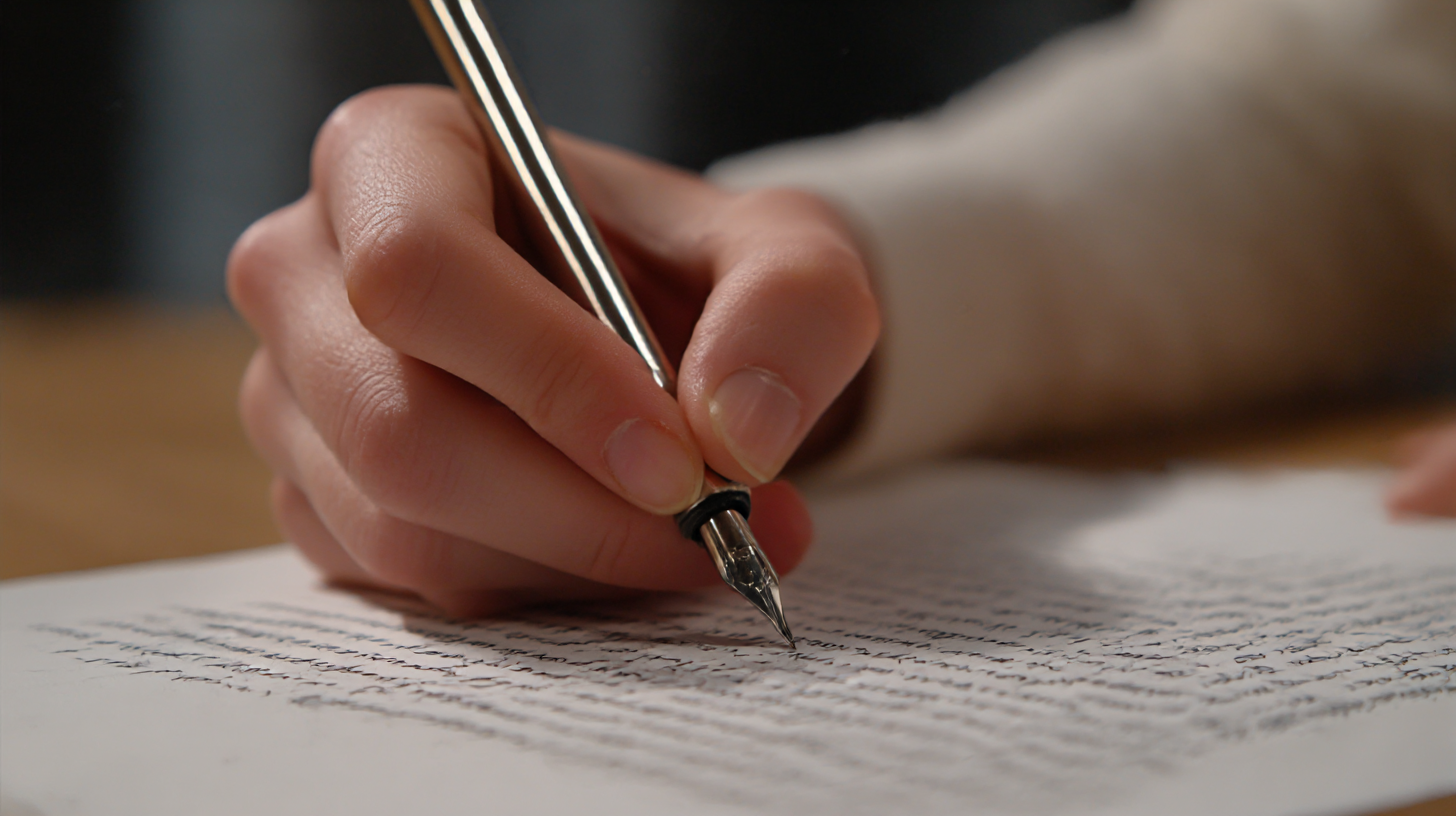
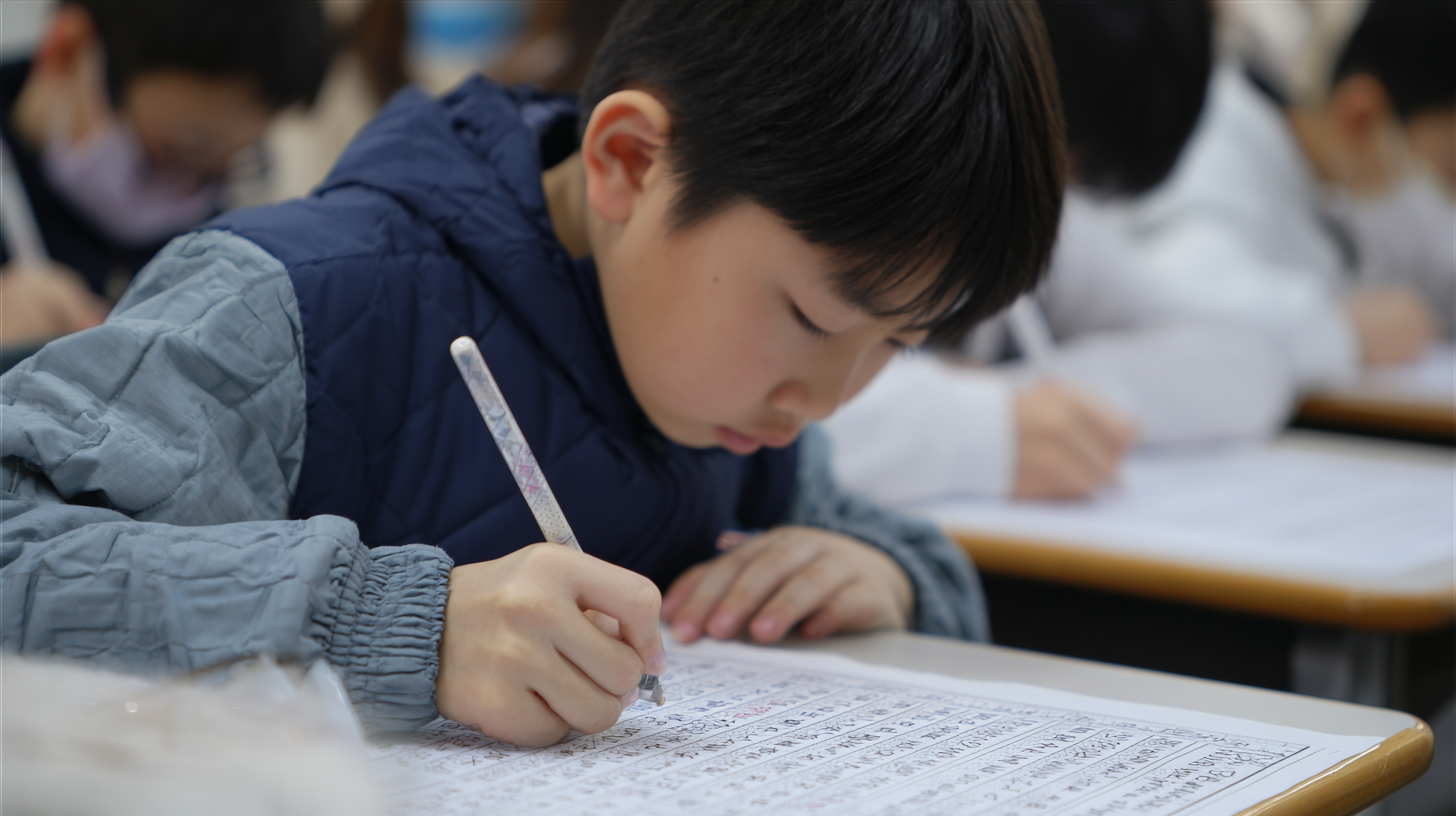
글씨 교정 - 초등학생 때부터 시작해야 하는 이유 아이들의 글씨체는 초등학생 시기에 형성되기 시작해요. 이때 잘못된 습관이 들면 어른이 되어서도 글씨를 교정하기 어려워질 수 있어요. 🖊
어릴 때부터 글씨를 바르게 쓰는 연습을 하면 평생 예쁜 글씨체를 유지할 수 있을 뿐만 아니라, 집중력과 학습 능력 향상에도 도움이 된답니다! ✍
그렇다면 초등학생 때 글씨 교정을 시작해야 하는 이유와 효과적인 연습 방법에 대해 알아볼까요? 🚀
📝 초등학생 시기의 글씨체 형성 과정
초등학생 시기는 손글씨가 본격적으로 형성되는 중요한 시기예요. 이때 바른 필기 습관을 들이면 평생 깔끔한 글씨체를 유지할 수 있답니다! ✍
보통 아이들은 만 4~5세 무렵부터 글자를 따라 쓰기 시작해요. 하지만 이때는 아직 손 근육이 완전히 발달하지 않아 글씨가 삐뚤빼뚤할 수밖에 없어요. 초등학교에 입학하면서부터 본격적으로 글씨를 배우고, 이 시기에 올바른 글쓰기 습관을 들이는 것이 매우 중요해요. 📚
초등 저학년(1~2학년) 때는 손가락 힘을 기르고 획을 정확하게 긋는 연습을 많이 해야 해요. 고학년(3~6학년)이 되면 글씨를 빠르게 써야 할 일이 많아지므로 이 시기까지는 글씨의 균형과 가독성을 높이는 연습을 충분히 해두는 것이 좋아요. ✏
📊 초등학생 글씨체 발달 과정
연령 특징 추천 연습법 4~5세 기본적인 선과 원 그리기 가능 색칠하기, 점 잇기 놀이 6~7세 글자를 따라 쓰기 시작 획을 정확히 긋는 연습 8~9세 (초등 저학년) 글씨체가 점차 안정됨 글자 크기와 간격 맞추기 연습 10~12세 (초등 고학년) 필기 속도가 빨라지며 글씨체 습관이 고정됨 균형 잡힌 필기 연습, 필사하기 초등학생 시기에 글씨 연습을 충분히 하면 성인이 되어서도 깔끔한 필체를 유지할 수 있어요. 😊 그렇다면 왜 초등학생 때부터 글씨 교정을 시작해야 할까요? 다음에서 알아볼게요! 🚀
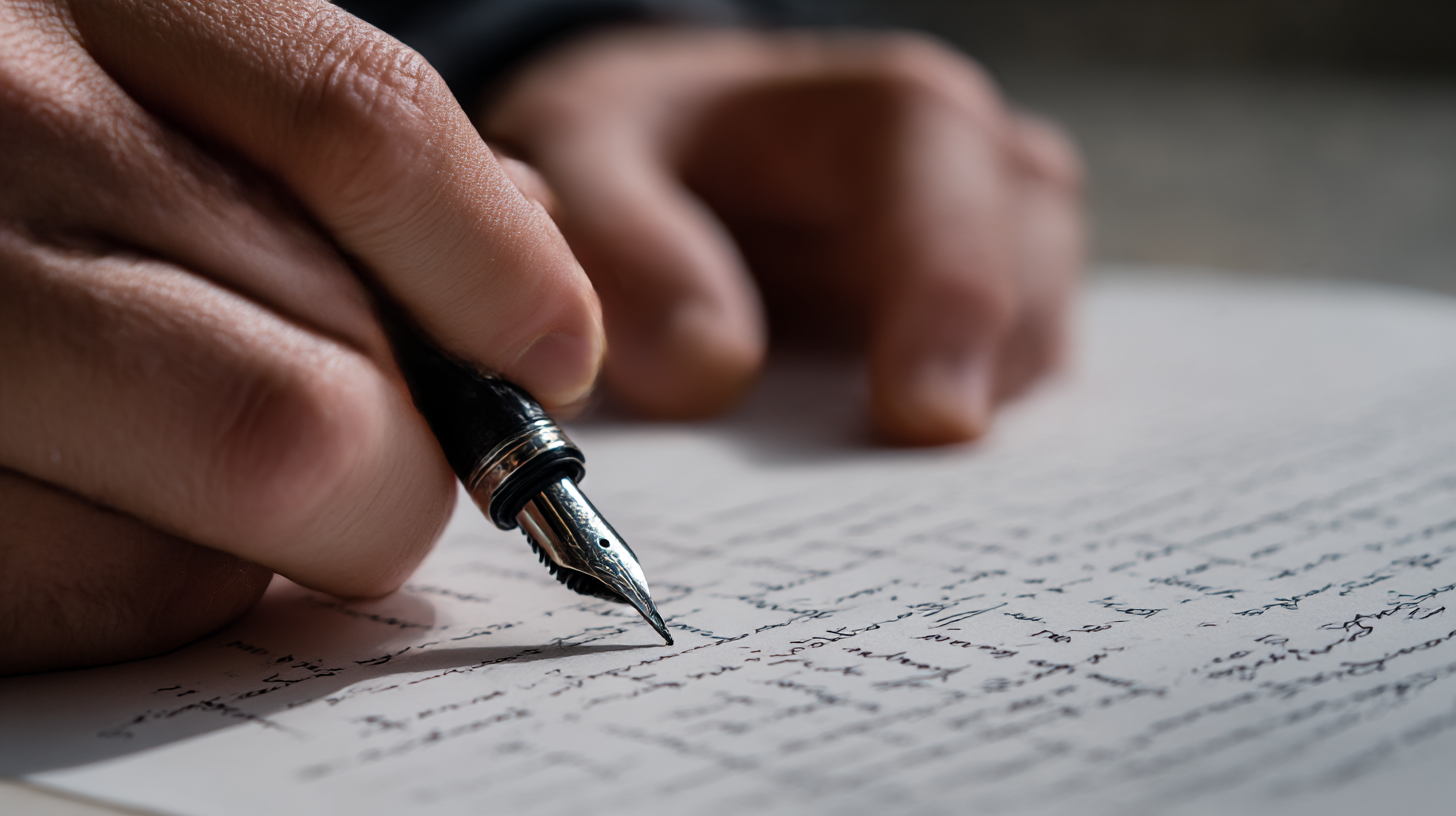
초등학생 시기의 글씨체 형성 과정 🎯 어릴 때 글씨 교정을 시작해야 하는 이유
글씨 교정은 빠르면 빠를수록 좋아요! 특히 초등학생 시기에 바른 필기 습관을 들이면 성인이 되어서도 예쁜 글씨체를 유지할 수 있답니다. ✍
어릴 때 글씨를 교정해야 하는 가장 큰 이유는 '근육 기억'과 '필기 습관'이 형성되기 때문이에요. 글씨를 쓰는 것은 단순한 손 움직임이 아니라 손과 뇌가 연결된 하나의 패턴이에요. 🧠✋
즉, 초등학생 때 글씨를 잘못된 방식으로 쓰기 시작하면 그 습관이 그대로 굳어버려서 나중에 교정하기가 더 어려워져요. 반대로, 어릴 때부터 바른 글씨체를 익히면 오랫동안 유지할 수 있어요. 😊
📌 어릴 때 글씨 교정을 하면 좋은 점
이유 설명 근육 기억 형성 손이 자연스럽게 올바른 글씨체를 기억함 필기 속도 향상 글씨를 빠르고 정확하게 쓸 수 있음 자신감 증가 깔끔한 글씨로 인해 학습에 대한 자신감 상승 평생 유지 가능 한 번 익힌 글씨체는 쉽게 바뀌지 않음 이처럼 어릴 때부터 글씨를 교정하면 시간이 지나도 변하지 않는 좋은 습관을 가질 수 있어요. 그렇다면 초등학생들이 효과적으로 글씨를 교정하는 방법은 무엇일까요? 🎯
📖 초등학생을 위한 효과적인 글씨 교정법
초등학생이 글씨를 교정하려면 단순히 많이 써보는 것만으로는 부족해요. 올바른 방법으로 꾸준히 연습해야 손에 익고, 자연스럽게 예쁜 글씨체가 형성된답니다! ✍
특히 어린아이들은 손 근육이 아직 완전히 발달하지 않았기 때문에 글씨를 쓸 때 힘 조절이 어렵고, 쉽게 피곤해질 수 있어요. 그래서 글씨 연습을 할 때는 재미있고, 무리 없는 방법으로 접근하는 것이 중요해요! 😊
✏ 효과적인 초등학생 글씨 교정법
연습법 방법 효과 점선 따라 쓰기 글자의 점선을 따라 쓰면서 형태 익히기 획의 방향과 균형 익히기 모눈 종이에 쓰기 모눈 칸을 활용해 글자 크기와 간격 맞추기 균형 잡힌 글씨체 연습 큰 글씨부터 작은 글씨로 처음에는 크게 쓰고 점점 작은 글씨로 연습 손 근력 강화 & 글씨 조절 능력 향상 필사 연습 짧은 문장을 따라 쓰면서 글씨체 익히기 자연스러운 필기체 형성 이러한 연습법을 활용하면 초등학생도 재미있게 글씨를 교정할 수 있어요! 그렇다면 글씨체를 예쁘게 유지하려면 어떤 필기 습관을 가져야 할까요? 🎯
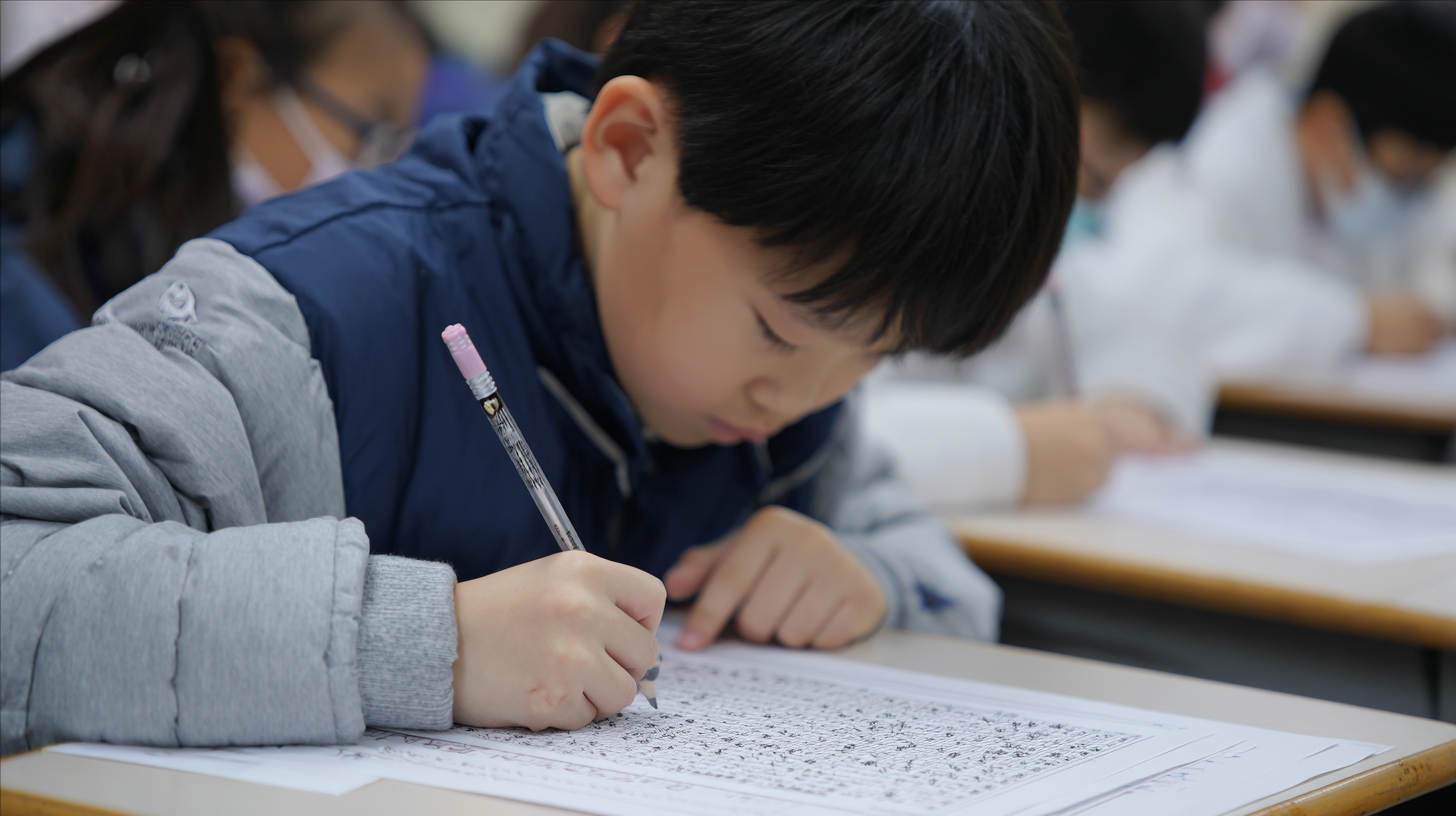
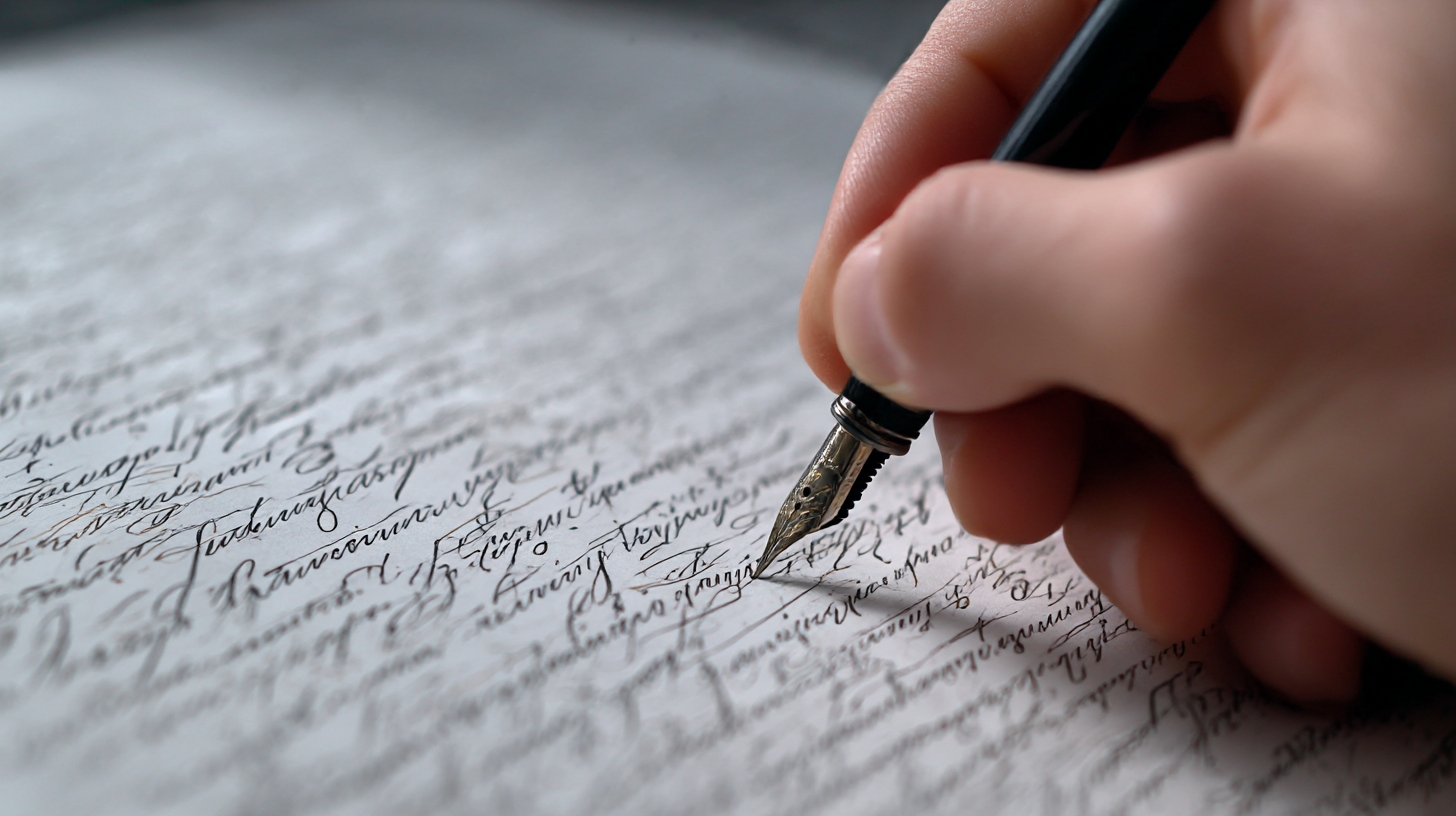
초등학생을 위한 효과적인 글씨 교정법 📌 바른 글씨체를 위한 필기 습관
예쁜 글씨를 쓰려면 올바른 필기 습관을 갖는 것이 중요해요. 아무리 많은 연습을 해도 필기 습관이 잘못되어 있다면 글씨가 쉽게 흐트러지고, 일정한 글씨체를 유지하기 어려워요! ✍
특히 초등학생들은 글씨를 빠르게 쓰려고 하다가 손에 힘이 너무 많이 들어가거나, 바른 자세를 유지하지 못하는 경우가 많아요. 따라서 필기 습관을 교정하는 것이 예쁜 글씨체의 첫걸음이에요. 😊
📝 올바른 필기 습관 체크리스트
필기 습관 설명 효과 바른 자세 유지 허리를 곧게 펴고, 책상과 눈의 거리를 일정하게 유지 손목 피로 감소 & 글씨 안정성 향상 적절한 필기구 사용 자신의 손에 맞는 필기구를 선택하여 사용 글씨의 균형 유지 & 편안한 필기 손에 힘을 빼고 쓰기 필기할 때 손목과 손가락의 힘을 적절히 조절 부드러운 필기체 형성 천천히 쓰는 연습 속도를 줄여 글자 하나하나 정확하게 쓰기 획이 일정하고 깔끔한 글씨 완성 이러한 습관을 꾸준히 유지하면 자연스럽게 글씨가 예뻐지고, 오래도록 균형 잡힌 필체를 유지할 수 있어요! 😊 그렇다면 초등학생들이 글씨를 연습할 때 어떤 필기구를 사용하면 좋을까요? 다음에서 알아볼게요! 🎯
✏ 초등학생 글씨 교정에 좋은 필기구 추천
올바른 필기구를 선택하는 것도 글씨 교정에 중요한 요소예요. 특히 초등학생들은 손 근력이 충분히 발달하지 않았기 때문에 손에 잘 맞는 필기구를 사용하는 것이 좋아요. 😊
너무 미끄러운 펜을 사용하면 글씨가 흔들리고, 너무 두꺼운 필기구를 사용하면 손이 쉽게 피로해질 수 있어요. 따라서 적절한 필기구를 선택하는 것이 중요하답니다! ✍
🖊 추천 필기구 리스트
필기구 종류 특징 추천 이유 연필 (2B~4B) 부드럽게 써지고 손에 무리가 적음 악필 교정 초기 연습에 적합 그립 연필 손가락 위치를 잡아주는 디자인 바른 필기 습관 형성에 도움 유성 볼펜 필기감이 부드럽고 미끄러지지 않음 속기 연습에 적합 만년필 필압을 조절하며 쓰는 연습 가능 필기 습관을 정교하게 교정 이처럼 초등학생의 필기 습관과 손 근력에 맞는 필기구를 사용하면 더 편안하고 안정적인 글씨체를 만들 수 있어요. 😊 그렇다면 부모님은 아이들의 글씨 교정을 위해 어떤 도움을 줄 수 있을까요? 다음 섹션에서 알아볼게요! 👨👩👧👦
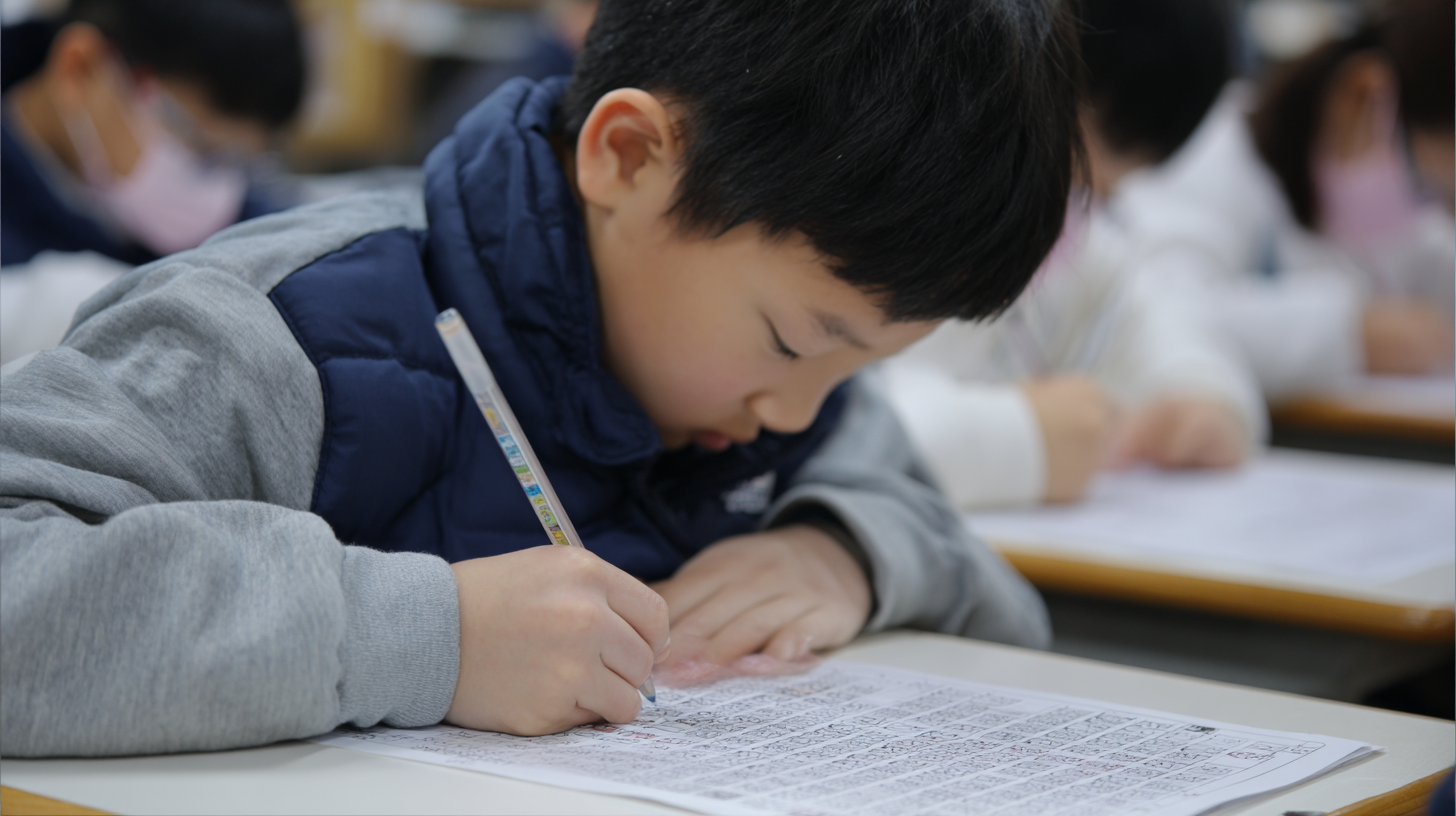
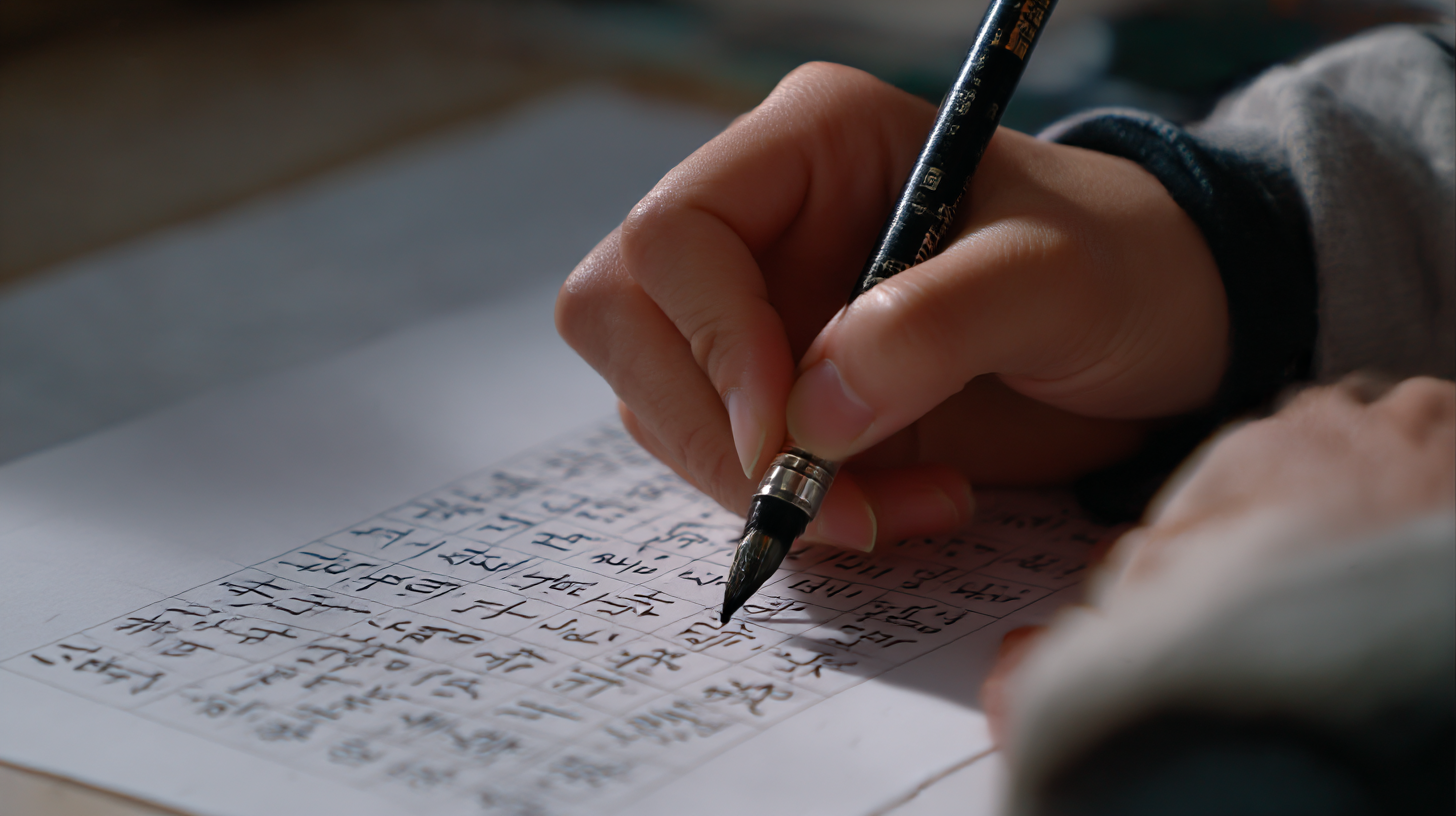
초등학생 글씨 교정에 좋은 필기구 추천 👨👩👧👦 부모님이 도와줄 수 있는 글씨 교정 팁
아이의 글씨 교정은 단순한 반복 연습만으로는 해결되지 않아요. 부모님의 올바른 지도와 격려가 함께한다면 아이들이 더욱 재미있고 효과적으로 글씨를 교정할 수 있답니다! ✍
특히 초등학생들은 오랫동안 집중하기 어려우므로 강압적인 방식보다는 흥미를 유도하며 연습할 수 있도록 도와주는 것이 좋아요. 😊
💡 부모님이 도와줄 수 있는 방법
방법 설명 기대 효과 칭찬과 격려 잘한 부분을 칭찬하며 연습 의욕을 높이기 아이의 자신감 상승 재미있는 필사 연습 아이들이 좋아하는 동화책이나 만화를 따라 쓰기 글쓰기 흥미 유발 올바른 자세 지도 글씨를 쓸 때 자세와 필기구 잡는 법 점검 바른 필기 습관 형성 필기 도구 선택 도움 아이 손에 맞는 필기구 추천 필기 편안함 & 손 피로 감소 부모님의 작은 관심과 배려만으로도 아이들은 글씨 쓰기에 대한 흥미를 가질 수 있어요. 너무 부담을 주기보다는 즐겁게 연습할 수 있도록 지도해주세요! 😊
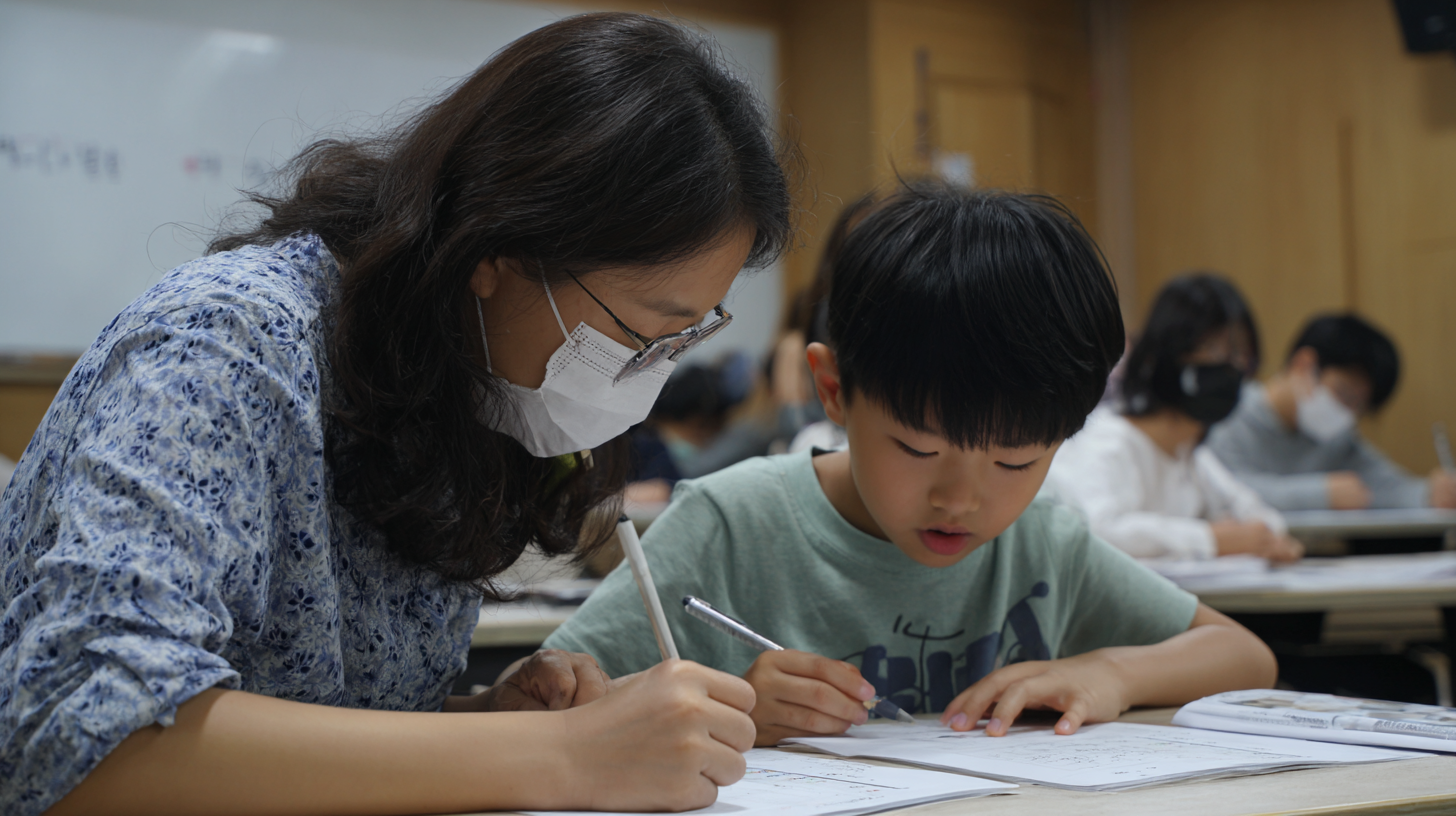
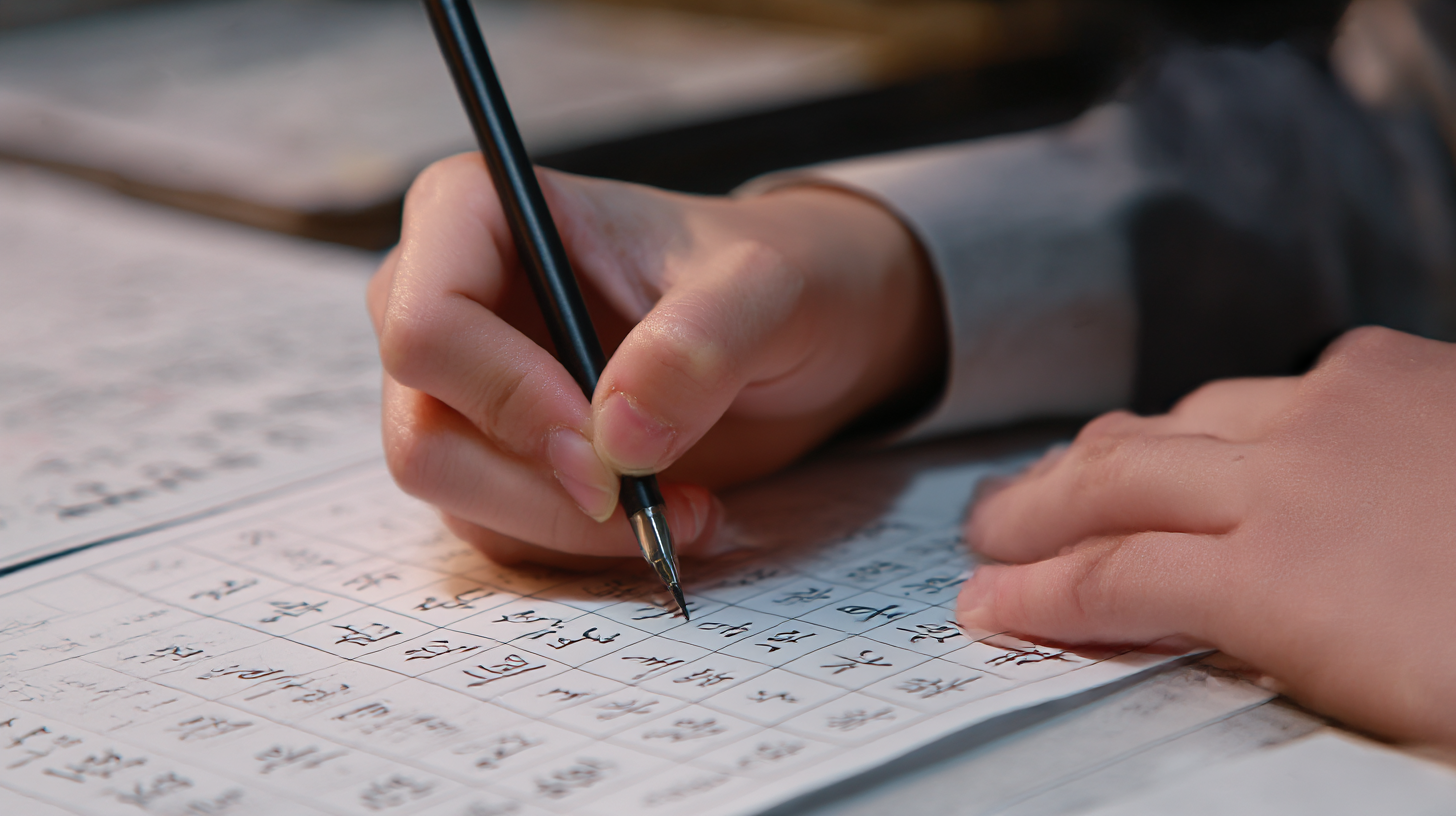
부모님이 도와줄 수 있는 글씨 교정 팁 ❓ FAQ
Q1. 초등학생이 글씨 교정을 시작하기에 가장 좋은 시기는 언제인가요?
A1. 초등학교 1~2학년이 가장 좋은 시기예요. 이 시기는 글씨체가 형성되는 단계이기 때문에 바른 습관을 들이기에 최적의 시기랍니다! ✍
Q2. 글씨 교정을 위해 하루에 얼마나 연습해야 하나요?
A2. 하루 15~30분 정도가 적당해요. 너무 오래 연습하면 손이 피로해지고 흥미를 잃을 수 있으니 적절한 시간 동안 꾸준히 연습하는 것이 중요해요. ⏳
Q3. 초등학생이 연습하기 좋은 글씨 교정 방법은 무엇인가요?
A3. 점선 따라 쓰기, 모눈 종이 연습, 필사 연습 등이 좋아요. 특히 아이들이 좋아하는 동화책이나 만화를 따라 쓰게 하면 재미있게 연습할 수 있어요! 📖
Q4. 글씨를 너무 빨리 쓰는 습관을 고치는 방법이 있나요?
A4. 속도를 줄이고 천천히 쓰는 연습을 해보세요. 또한, 줄 간격이 있는 공책을 사용하면 글씨 크기와 속도를 조절하는 데 도움이 돼요! 😊
Q5. 글씨를 쓸 때 손에 힘이 너무 많이 들어가는 경우 어떻게 해야 하나요?
A5. 손 스트레칭을 자주 해주고, 필기구를 너무 꽉 잡지 않도록 신경 써보세요. 너무 딱딱한 연필보다는 부드러운 필기구(2B 연필 등)를 사용하는 것도 좋아요. ✋
Q6. 부모님이 아이의 글씨 교정을 도울 때 주의해야 할 점은?
A6. 강요보다는 흥미를 유도하는 것이 중요해요! 칭찬을 많이 해주면서 아이가 부담 없이 즐겁게 연습할 수 있도록 도와주세요. 🎉
Q7. 초등학생이 연습하기 좋은 필기구는 어떤 것이 있나요?
A7. 2B~4B 연필, 그립 연필, 부드러운 유성 볼펜이 좋아요. 필기구가 너무 미끄럽거나 두꺼우면 손이 쉽게 피로해질 수 있어요! ✏
Q8. 글씨 교정 효과를 빠르게 볼 수 있는 방법이 있나요?
A8. 하루 15~30분씩 꾸준히 연습하는 것이 가장 효과적이에요! 모눈 종이에 연습하거나, 글씨 교정 노트를 활용하면 빠르게 개선될 수 있어요. 🚀
초등학생 때부터 올바른 필기 습관을 기르면 평생 깔끔하고 예쁜 글씨체를 유지할 수 있어요. 꾸준한 연습과 올바른 지도만 있다면 누구나 멋진 글씨체를 가질 수 있답니다! 😊